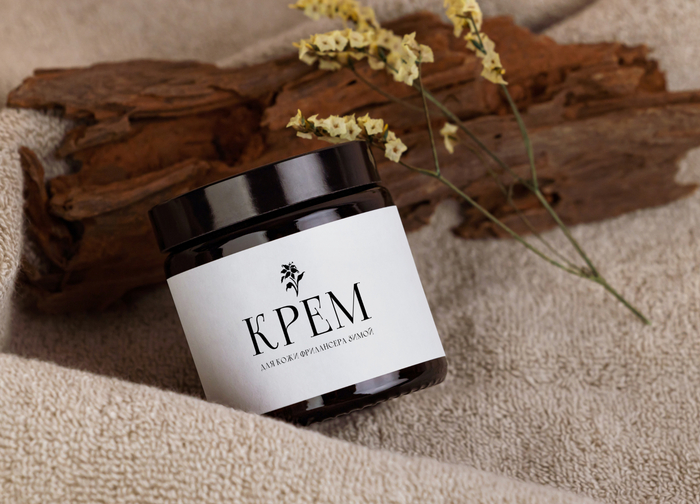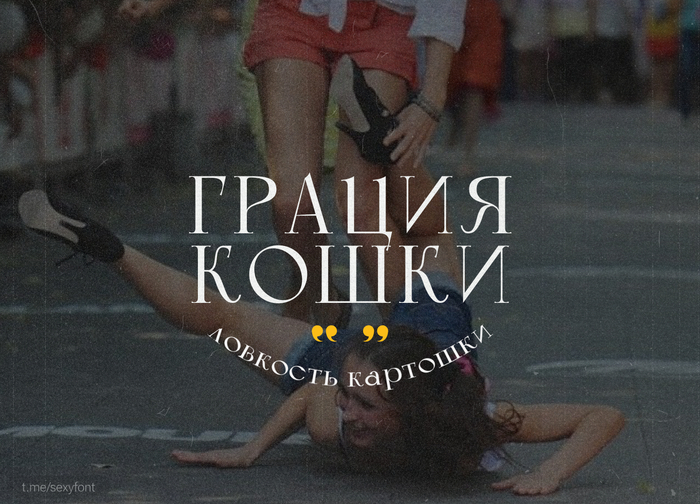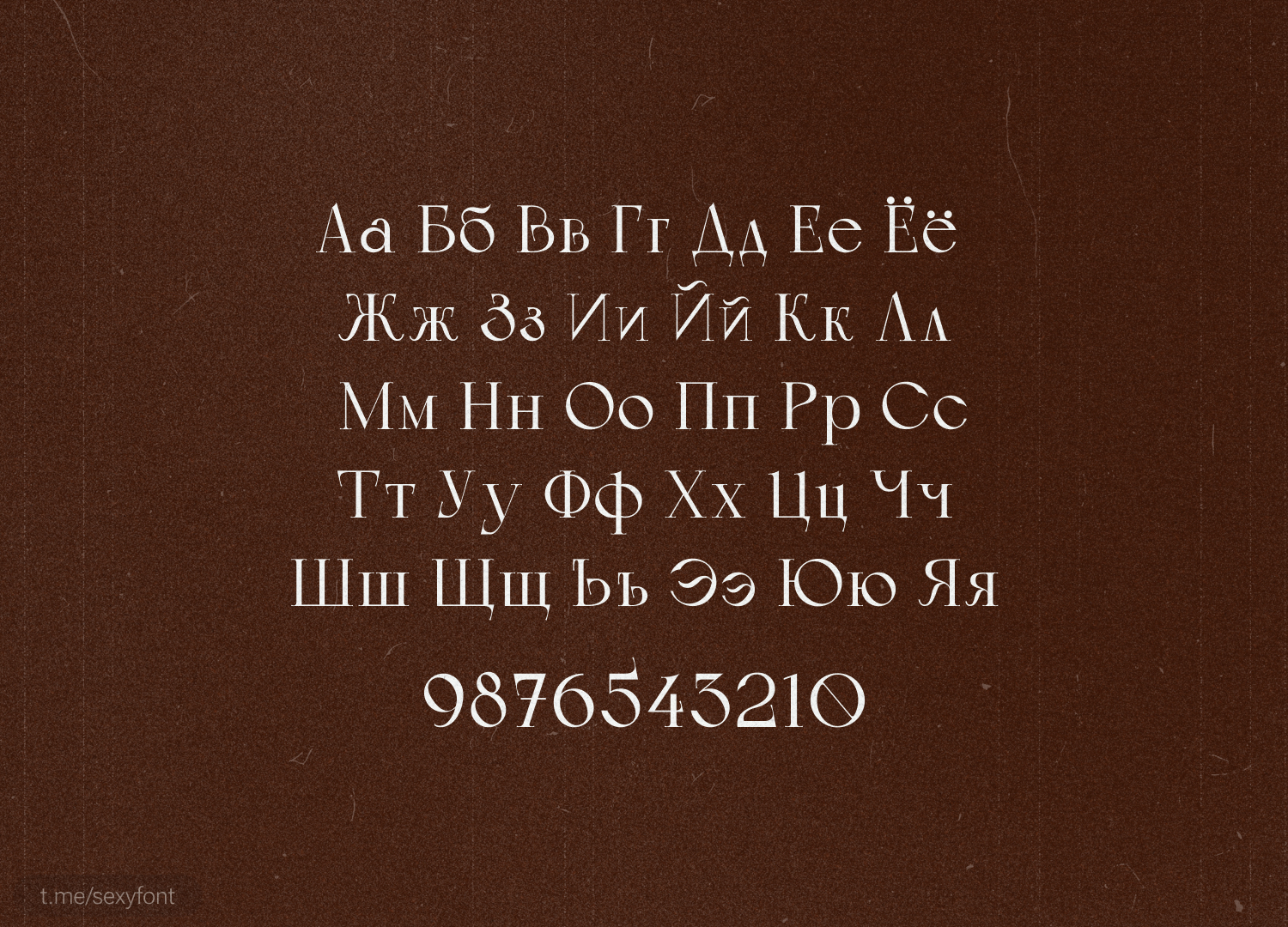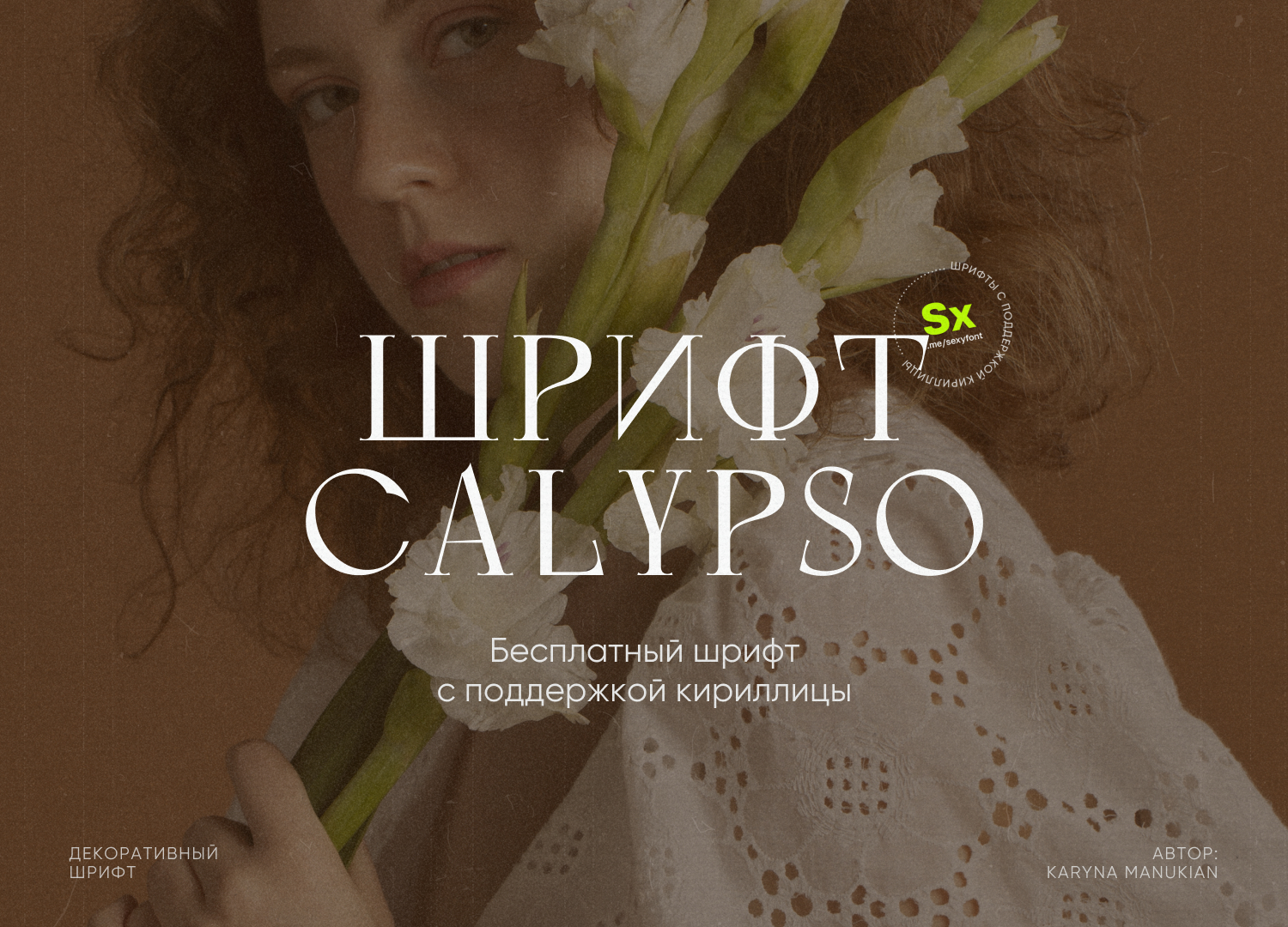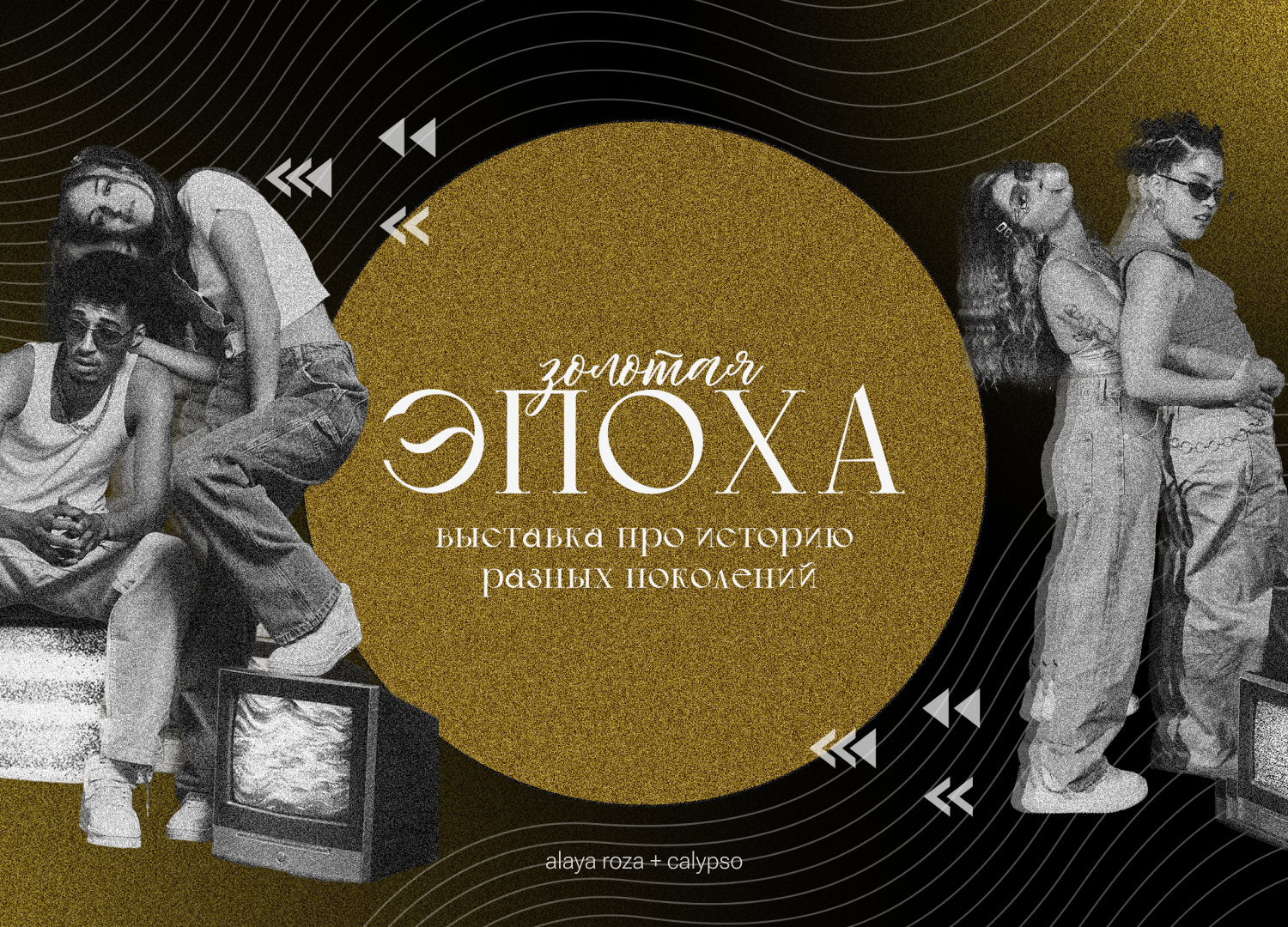
Шрифт Calypso. Кириллица
Подходит для заголовков, короткого, среднего или длинного текста. Калипсо включает латинские и кириллические символы, цифры и знаки и имеет один стиль.